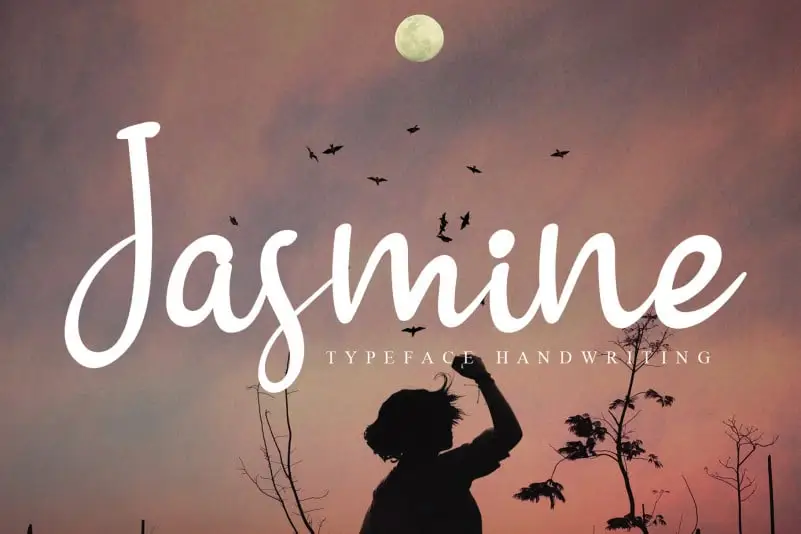
Jasmine Script Font – Fonte Grátis
Jasmine Script Font
A Jasmine Script Font é uma elegante e descontraída fonte de escrita manuscrita. Perfeita para aqueles que desejam dar um toque único a seus projetos digitais, essa fonte suave e fashion pode transformar qualquer design em um destaque. Suavemente fluente e relaxada, ela é perfeitamente adequada para criar texturas interessantes e estilos únicos no seu site, aplicativo ou identidade visual. Seja você uma marca inovadora ou designer que busca adicionar um toque único a seus projetos, Jasmine Script Font é definitivamente a escolha certa. Engane-se em deixar de lado essa fonte poderosa para trazer beleza e conforto à sua interface digital.